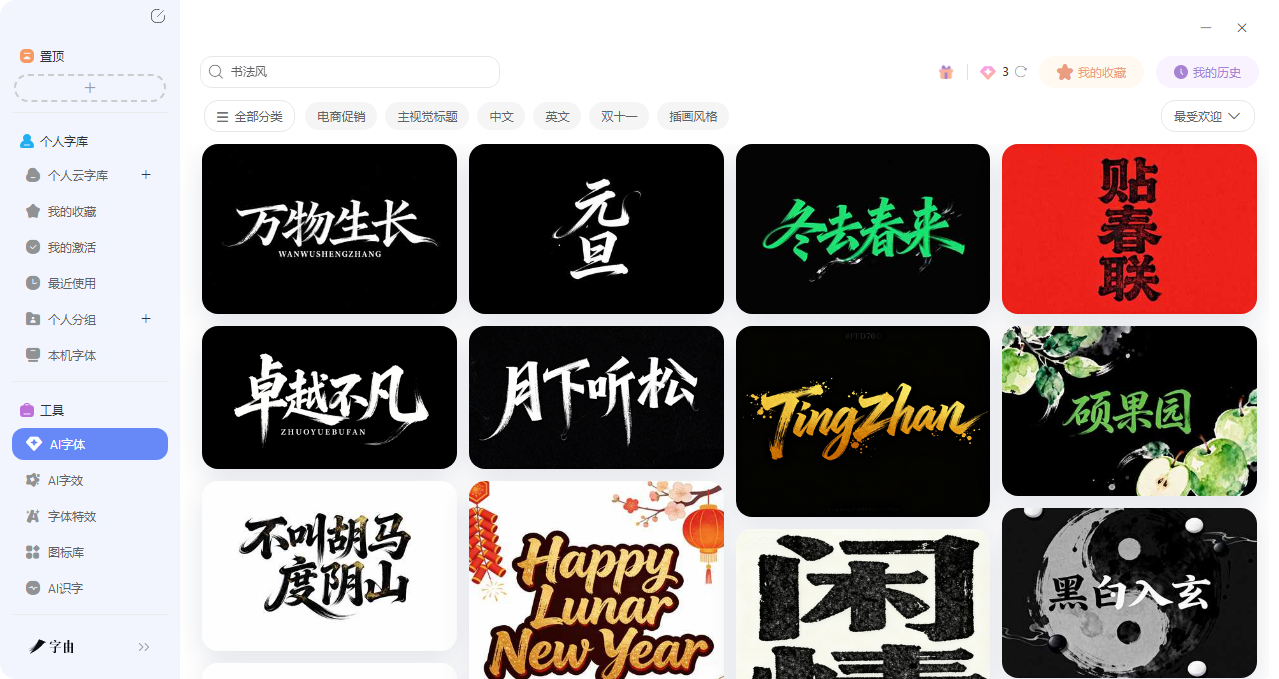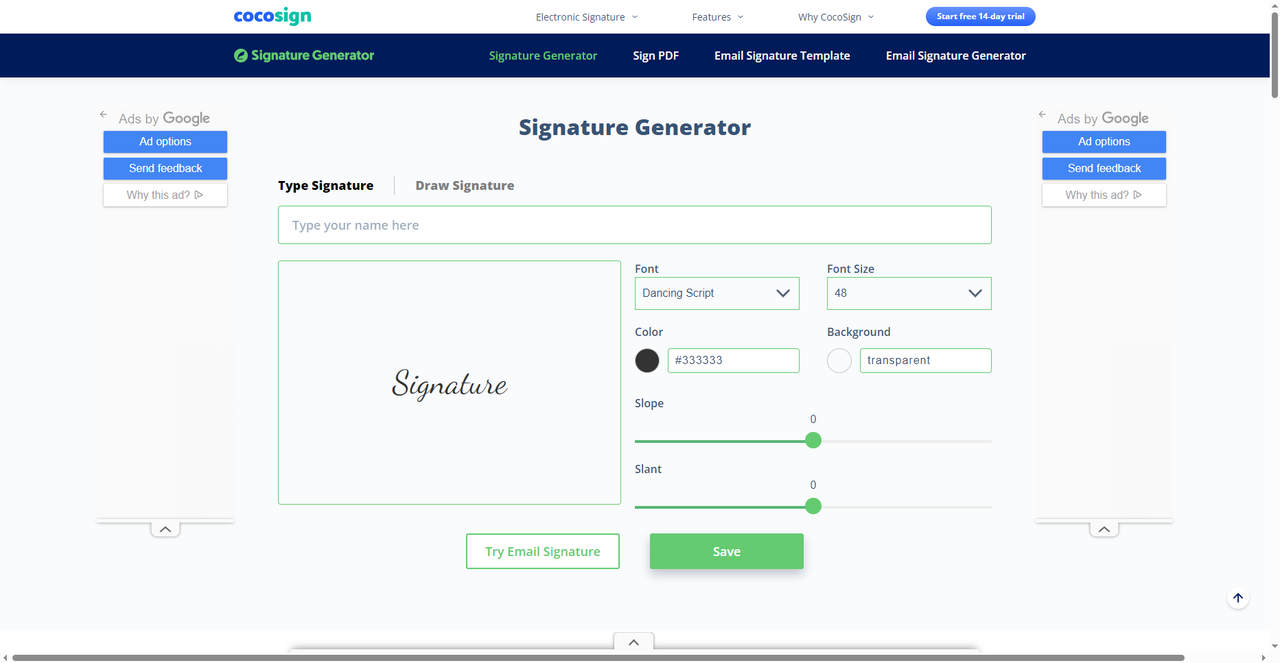
5个姓名艺术签名设计网站推荐,高效快捷,一键出图
签名这个概念在我很小的时候就有了,一开始是看大人们签字,自己也想要一个帅气的专属签名。长大以后发现这件事确实很重要,因为不仅是签合同,签各种东西的时候,好看的字体会给人留下深刻的印象,因此签名也成了个人IP的一部分。但是大部分人其实是不懂设计的,基本上都会对自己的手写签名不太满意——要么太潦草像鬼画符,要么太规整没有特色。想设计一个好看的签名,又不知道从哪下手。好在今天我会为大家推荐 5 个好用的姓名艺术签名设计网站,每个网站都各具特色,需要的话不要忘记收藏!
第一个要推荐的姓名艺术签名设计工具是字由,字由不仅仅是一个字体工具,同时也可以帮你搞定签名设计。签名的核心就是“字”,而字由最不缺的就是好字体。
在字由里,我会推荐你三种方式来选择自己的签名:
第一种:直接从字体库中挑选
字由拥有超过 10500 款精选字体,其中包含大量适合签名的书法体、手写体、艺术体。比如“江西拙楷”带着朴拙的手工感,“字由芳华体”笔画柔和适合文艺风,“字由文艺黑”既有黑体的稳重又带手写感。你可以在字由客户端里慢慢翻,找到喜欢的风格,然后在PS、AI 等软件里用这个字体打出你的名字,稍作调整就能变成专属签名。这是比较简便的方式。
第二种:AI生成签名
字由的AI字体功能,可以直接用来生成签名风格的文字。操作很简单:
• 打开字由客户端,找到【工具】下的【AI字体】
• 浏览各种字体模板(有书法风、手写风、艺术字等分类)
• 选中喜欢的模板,点击“做同款”
• 输入你的姓名
• 点击“立即生成”,等30秒左右就能得到设计好的签名文字
第三种:个人云字库存签名素材
虽然第三种不算是常规意义上的签名生成,但是能够很好地帮你保存你试过的、喜欢的字体,如果你哪天突然想换风格了也不用担心字体找不到,可以直接来字由的个人云字库来找你收藏过的字体。并且你也不用担心丢失问题,只要你的账号还在你的字体肯定就还会在。
2、Paperform
Paperform 是一个主打AI功能的姓名艺术签名设计工具。我们可以看到,它的界面非常简洁:左边是“Type”和“Draw”两个选项,中间是输入框,右边是生成按钮。
使用方法很简单:
• 在输入框里输入你的名字或首字母
• 点击“Generate with AI”
• 几秒钟后就能得到多个签名方案供选择
而且生成得到的签名可以直接下载,Paperform 的优势是速度快、操作简单,而且完全免费。如果你只是想快速看看自己的名字写成艺术签名是什么效果,这个工具值得一试。
3、CocoSign
CocoSign 是一个功能更丰富的签名生成工具。除了基础的“Type Signature”和“Draw Signature”两种模式,它还提供了很多调节选项:
• 字体选择:可以从下拉菜单里选不同风格的字体(比如 Dancing Script)
• 颜色调节:可以自定义字体颜色和背景颜色
• 倾斜度调节:可以调整签名的倾斜角度
这个姓名艺术签名设计工具的好处就是自由度比较高,因为这种细节调节功能,让你在生成签名后有更多的定制空间。如果你对默认生成的签名不太满意,想微调一下,CocoSign 会很适合。
4、Online Signature Generator
Online Signature Generator 里你可以选择两种设计签名的方式:
绘制模式:可以用鼠标、触摸板或手机屏幕手绘签名,支持调节平滑度和颜色,下载为 PNG 或 JPG。适合想要保留自己手写习惯的人。
输入模式:输入名字,从多种手写字体中选择喜欢的风格。字体库挺丰富,能满足大部分需求。
而且这个网站下滑还有一个很有意思的内容:名人签名欣赏。它提供了约翰·列侬、比尔·盖茨、沃伦·巴菲特、玛丽莲·梦露、甘地、奥巴马、莫扎特等名人的签名示例。如果你签名没有灵感的话可以看看名人们的签名风格。
5、Signaturely
Signaturely 是一个功能更全面的平台,不仅提供姓名艺术签名设计,还能直接签署文档。从首页图来看,我们能知道它同样提供了“Draw”和“Type”两种模式。这个和上面推荐的网站用法差不多,这里就不再过多介绍。生成签名后,可以直接在平台上签署PDF、Word等文档,对于经常需要处理电子合同的用户来说非常方便。它还提供了一些关于签名性格分析的趣味内容,比如“签名字迹潦草代表思维敏捷”“清晰易读代表性格透明”等,虽然不一定是科学,但看着挺有意思。